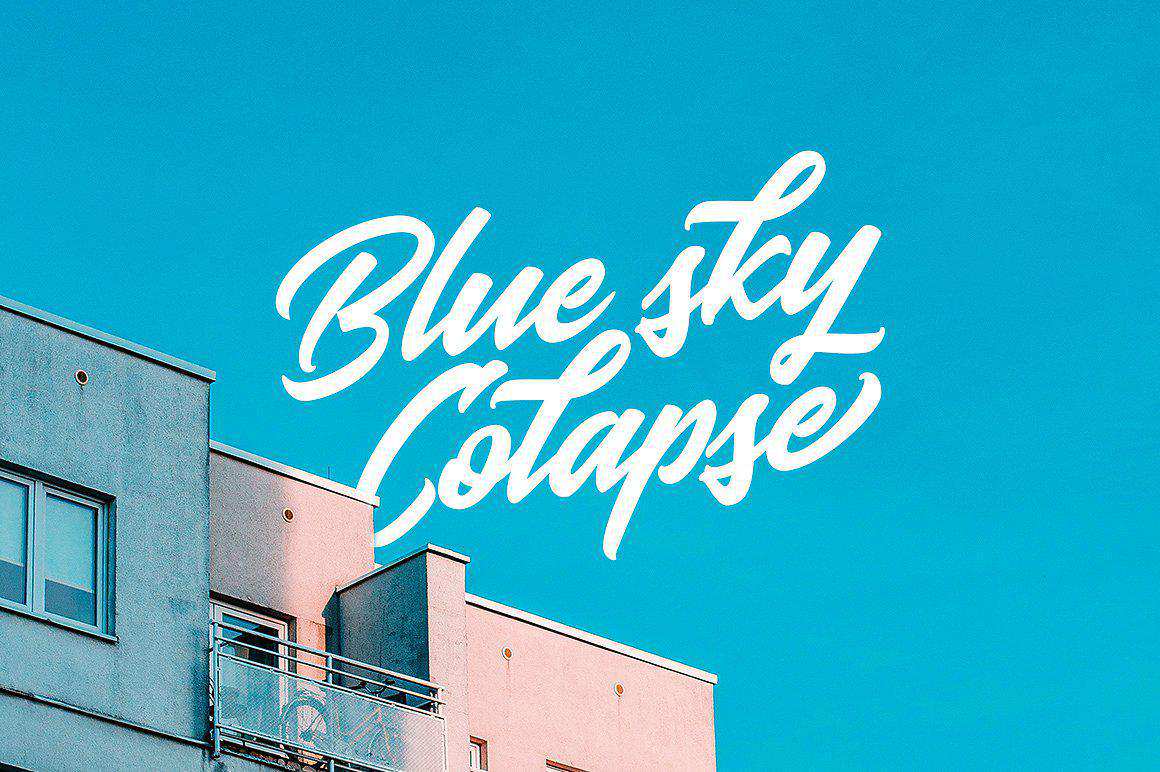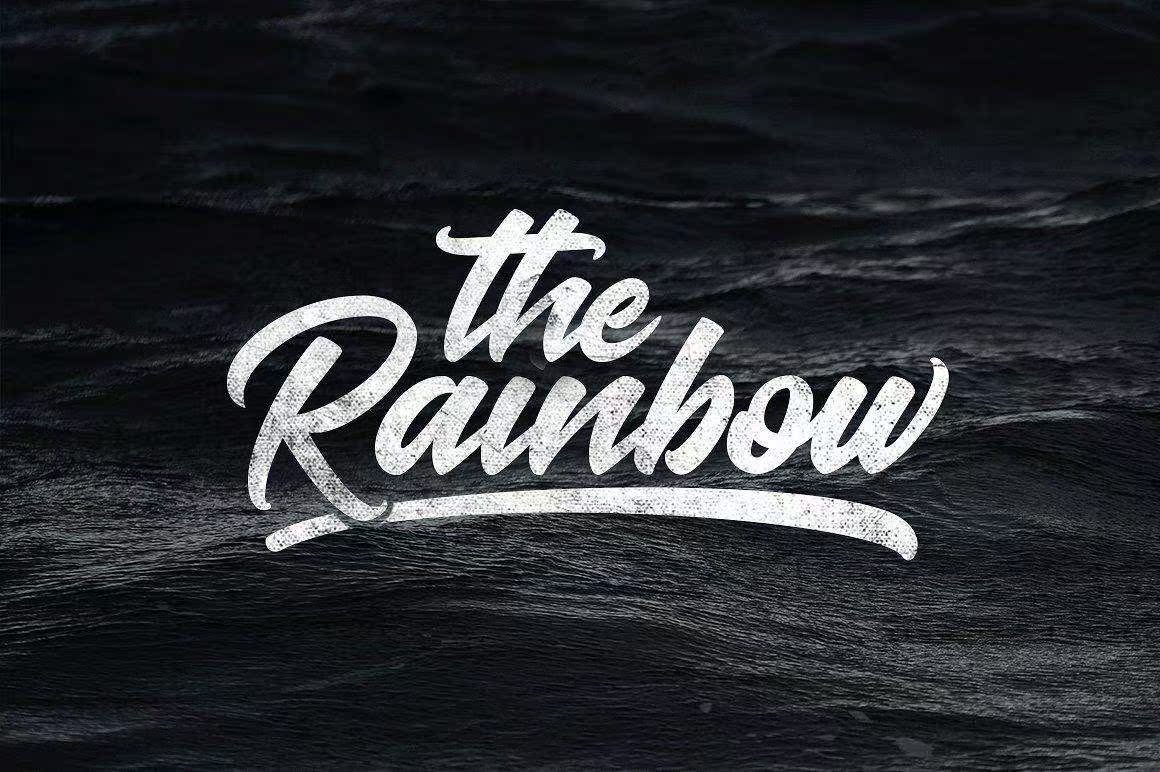
Baksodaisa和LetteringScriptFontwithacearStyleand戏剧性的移动此Fonts适用于您的下一个创意项目,如徽标、打印报价、邀请、卡片、产品包装、标题、徽标、信头、海报、装置标志、标签、,andetc.Baksodaisa和LetteringScriptFontwith acearstyle and戏剧性动作此Fonts适用于您的下一个创作项目,如徽标、打印报价、邀请函、卡片、产品包装、标题、徽标、信头、海报、装置标志、标签等。